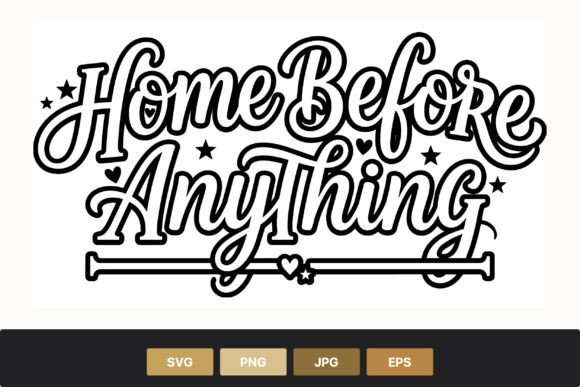
Home Before Anything Script Letters
適切なデザイン要素を見つけるのは難しい場合がありますが、Home Before Anything Script Lettersは作品を即座に引き立てる優れたコレクションを提供します。
POD(オンデマンド印刷)製品、結婚式の招待状、またはソーシャルメディアのグラフィックを作成している場合でも、Home Before Anything Script Lettersは理想的です。